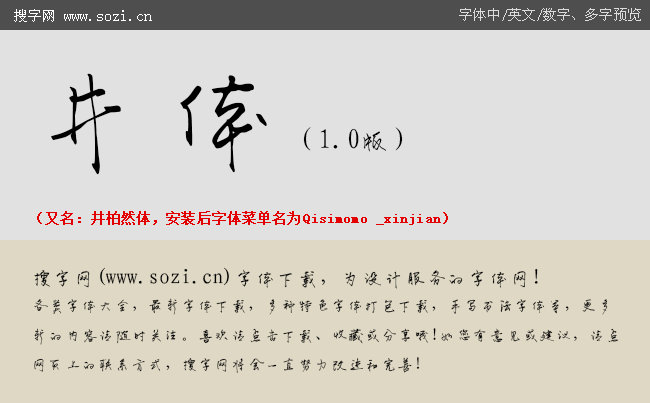
井體
搜字網(wǎng)提供一款井體手寫中文書法字體下載,井體是一款根據(jù)明星井柏然手寫字體制作的字體,井柏然字體非常鏗鏘有力,給人一種力量,文字非常優(yōu)美,整體效果非常出眾,能夠應(yīng)用于平面設(shè)計(jì)、名片設(shè)計(jì)、廣告創(chuàng)意、印刷包裝等領(lǐng)域。